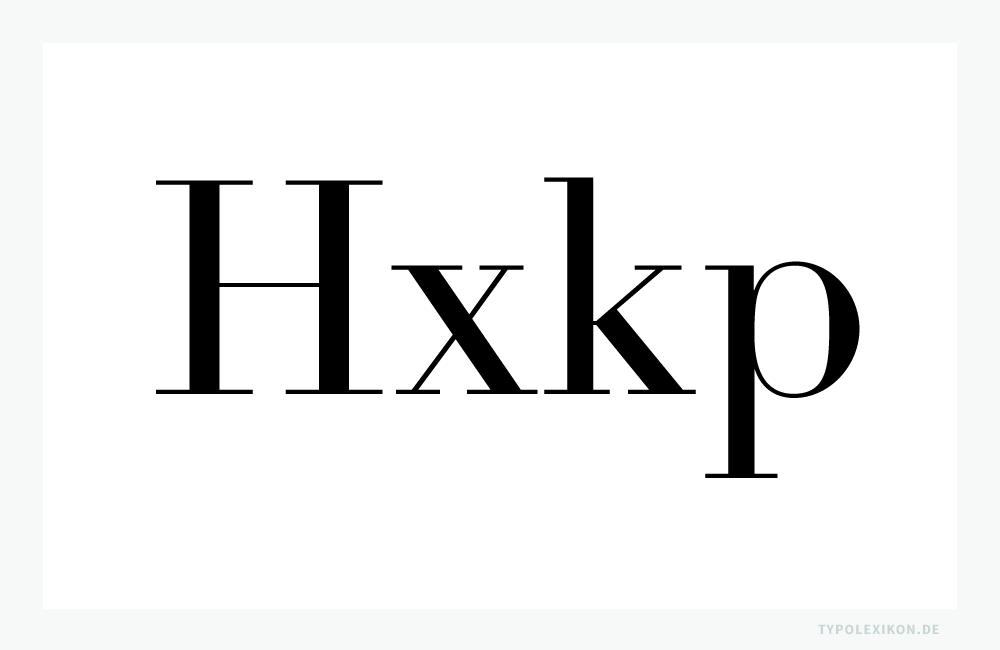
Klassizistische Antiqua
Schriftart; Schriftuntergruppe, die im Sinne der typografischen Schriftklassifikation zur Hauptschriftgruppe der Antiqua gehört; rundbogige Druckschrift römischen Ursprungs mit Serifen. Im englischsprachigen Raum als »Didone« bezeichnet.
Unter »Klassizistisch« bzw. »Klassizismus« wird ein westeuropäischer und nordamerikanischer Kunststil von 1750 bis ins frühe 19. Jahrhundert verstanden (Deutschland 1770–1830), der sich dadurch auszeichnet, die Formprinzipien der griechisch-römischen Antike in Kunst und Kultur nachzuahmen. In seiner typisch strengen Geradlinigkeit unterscheidet sich der Klassizismus wesentlich von der überbordenden Formenvielfalt des vorangegangenen Spätbarock bzw. Rokoko. Das Selbstverständnis dieses Stils: Logisch, klar, linear, streng und moralisierend. Politisch und gesellschaftlich symbolisierte der Klassizismus insbesondere die Demokratie des antiken Griechenlands und die römische Republik. So stellte er u.a. feudalistische Herrschaftsstrukturen und die »degenerierte Banausie« (Mirabeau) der Aristokratie in Frage und favorisierte das Ideal der liberalen Geisteshaltung eines humanistisch »aufgeklärten« Bildungsbürgertums (Gebrüder Humboldt). Der Klassizismus wurde deshalb zum führenden Kunststil junger Republiken wie Frankreich (Empire) und Nordamerika. Er galt ab den 1790er Jahren als »Stil der Revolution«. 1)
Etymologisch leitet sich der Begriff »Klassizismus« von »klassisch« ab, was aus dem mittellateinischen »classicus« für »mustergültig, vorbildlich, erstklassig « entlehnt ist, das wiederum auf das lateinische »classicus« (in normativer Hinsicht »die römische Bürgerklasse betreffend«) und »classis« zurückgeht, womit die »Klasse« als höchste, elitäre Gesellschaftsschicht der Antike gemeint war. Bereits im zweiten nachchristlichen Jahrhundert unterschied der römische Schriftsteller Aulus Gellius in seiner 20 Bände umfassenden griechisch-lateinischen Literaturgeschichte »Noctes Atticae « den »scriptor classicus«, also den erstklassigen Autor, Rhetor, Historiker oder Philosophen, schlicht: den Klassiker vom proletarischen Schreiberling. Im achtzehnten Jahrhundert wurde dieser Begriff dann auch auf nachantike Literaten und Künstler ausgedehnt, zuerst von Voltaire 1761, als er in einem seiner zahlreichen Artikel für Diderots »Encyclopédie« die bedeutendsten französischen Dichter des vorangegangenen Jahrhunderts – Corneille und Racine – als »Klassiker« bezeichnet.
Schriftprobe eines digitalen Remakes einer streng linear aufgebauten Klassizistischen Antiqua von Firmin Ambroise Didot (1764–1836) von Adrian Frutiger für Linotype aus dem Jahre 1991. Infografik: www.typolexikon.de
Schriftprobe eines digitalen Remakes einer streng linear aufgebauten Klassizistischen Antiqua von Firmin Ambroise Didot (1764–1836) von Adrian Frutiger (1928–2015) für Linotype aus dem Jahre 1991.
Die Bezeichnung »Antiqua« geht etymologisch auf die lateinische weibliche Form von »antiquus« zurück, für »vorig, alt«, eine Nebenform von »anticus« für »der vordere« vom lateinischen »ante« für »vor«. Mit »Antiqua« ist somit die »alte Schrift« gemeint. Die Antiqua ist heute die führende Verkehrsschrift der westlichen Welt.
Die Klassizistische Antiqua ist in ihrer Typometrie streng linearer aufgebaut. Sie verfügt über sehr starke Grundstriche, feine Haarlinien und feine, lange Serifen, welche waagrecht angesetzt sind und eckig abschließen. Die Schriftachse der runden Buchstabenformen steht präzise senkrecht.
Primäre Klassifikationsmerkmale
Dachansätze Majuskel: Gerade
Minuskeloberlängen: Enden bei der H-Linie, allerdings oft Dachansatz zur »Großen Überhangslinie«
Achse der Minuskel e: Waagrechter Innenbalken
Optische Achse der Rundformen: Senkrecht
Serifenübergänge: Eckig oder rund
Serifenseitenkante: Gerade
Serifenunterkante: Steht gerade auf der Grundlinie
Stichstärkenkontrast Balken/Querbalken: Sehr stark
Vertreter dieser Schriftart
SchriftSchriftgestalterFont FoundryJahr
Bauer BodoniJost, Heinrich
Höll, Lois
Bauer1926/1927
BodoniBodoni, GiambattistaStamperia realeum 1771
Bodoni Old FaceLange, Günter GerhardBerthold1983/2001
CaledoniaDwiggins, Wiliam A.Mergenthaler (Linotype)1939
CentennialFrutiger, AdrianLinotype1986
CenturyBenton, Linn BoydATF1894
DidotDidot, Firmin AmbroiseImprimerie Royaleum 1790
Didot LinotypeFrutiger, Adrian
Linotype Design Studio
Linotype1991
ElektraDwiggins, William A.Linotype1935
FeniceNovarese, AldoITC1977–1980
FilosofiaLicko, ZuzanaEmigre1996
Monotype ModernMonotype1860/1896
Prillwitz, Johann Carl LudwigGöschen/Bertuch1790
PrillwitzPreuss, IngopreussTYPE2006
Romain de L’Empereur
(Kaiser-Antiqua)
Didot, Firmin AmbroiseImprimerie Royale1804
WalbaumWalbaum, Justus ErichKircher/Walbaum/Bertuchum 1800
WalbaumLange, Günter GerhardBerthold1976
Ab cirka 1770 entwickelte der italienische »Principe dei tipografi« (»der Fürst unter den Typografen«) Giambattista Bodoni (1740–1813) aus der französischen Réales Pierre Simon Fourniers erstmals eine Klassizistische Antiqua mit einem streng symmetrischen, fast monumental anmutenden Aufbau, welche die westeuropäische Schriftkultur des gesamten 19. Jahrhunderts maßgeblich prägen sollte. Erstmalig wurde diese Schriftart von Bodoni in seinen »Epithalamia exoticis linguis reddita, Parmae, Regio typografeo MDCCLXXV« 2)  veröffentlicht, und in den darauf folgenden Jahren verfeinert.
Schriftprobe eines digitalen Remakes der Bodoni (Giambattista Bodoni, 1740–1813). In der Schriftklassifikation zählen Bodonis zu den Klassizistischen Antiquas. Infografik: www.typolexikon.de
Schriftprobe eines digitalen Remakes der Bodoni (Giambattista Bodoni, 1740–1813). In der Schriftklassifikation zählen Bodonis zu den reinen Klassizistischen Antiquas.
Schrift ist nicht gleich Schrift, auch wenn Schriften auf den ersten Blick ähnlich aussehen können oder vordergründig sogar den gleichen Namen tragen. Hier ein Rohsatzvergleich von vier Bodoni Antiquas im normalen Schriftschnitt. Die Typometrie unterscheidet sich signifikant voneinander. Infografik: www.typolexikon.de
Schrift ist nicht gleich Schrift, auch wenn Schriften auf den ersten Blick ähnlich aussehen können oder vordergründig sogar den gleichen Namen tragen. Hier ein Rohsatzvergleich von vier klassizistischen Bodoni Antiquas im normalen Schriftschnitt. Die Typometrie unterscheidet sich signifikant voneinander.
In Deutschland (damals Heiliges Römisches Reich Deutscher Nation 962–1806) war es vornehmlich der Leipziger (damals Kurfürstentum Sachsen) Typopgraph und Verleger Georg Joachim Göschen (1752–1828), der in den Jahren 1794 bis 1802 die Gesamtausgabe der Werke von Christoph Martin Wieland in der 1790 von Johann Carl Ludwig Prillwitz (1758–1810) geschnittenen ersten deutschen Klassizistischen Antiqua verlegte und in exemplarischer Weise die Eleganz der französischen Lettern von Firmin Didot (1764–1836) mit den buchtypografischen Stilvorgaben und Satzregeln, die Bodoni in seinem »Manuale tipografico« kanonisiert hatte, umsetzte. Zur Realisierung seiner makro- und mikrotypografischen höchst anspruchsvollen Formvorstellungen von einer ebenmäßigen, sogenannten »splendiden Satzweise« führte Göschen auch die dazugehörige Drucktechnologie ein: der Einsatz von Stegen und Pressen aus Metall anstelle von Holz gewährleistete das konsequente Halten der Schriftlinie, den exakten Axialsatz des Titelblatts und den gleichmäßigen Farbabdruck; ein optimiertes Schriftgußverfahren ermöglichte die präzisen und langgezogenen Haarstriche der neuen Antiqua-Schnitte; sorgfältigst ausgeschlossene Buchstaben- (Laufweite) und Wortzwischenräume, ein großer Zeilendurchschuß und die breiten Ränder des Satzspiegels sorgten für die regelmäßige Grauwirkung eines lichten, harmonischen Satzbildes, das insgesamt dem ästhetischen Ideal des klassizistischen Stils entsprach. Voll begeisterter Emphase schrieb Wieland 1793 in einem Brief an Göschen über den Probedruck der Prillwitz-Antiqua für die Ausgabe seiner Werke: »Ich kann mich nicht genug an der Schönheit dieser Lettern ergötzen! Eine jede ist in ihrer Art eine Mediceische Venus. Lachen Sie nicht über die anscheinende Hyperbole! Es ist etwas Wahres an dieser seltsam tönenden Behauptung; ich wenigstens kann mir keine schöneren Schriftzeichen denken als diese, und ich habe doch auch eine Imaginazion …«
1804 schuf Firmin Didot in Paris für die offiziellen Dokumente zur Kaiser-Krönung von Napoleon Bonaparte den nur dieses eine Mal verwendeten Schriftschnitt »Romain de L’Empereur« ( »Kaiser-Antiqua« ). Diese exklusive Klassizistische Antiqua präsentierte als typografisches und kulturpolitisch gleichermaßen brisantes Kuriosum die englischen, üblicherweise hochgestellten Anführungszeichen in der niedrigeren Position der traditionellen französischen Guillemets, also »99/66« in Minuskelhöhe: wohl als »diakritisch« subtile Anspielung darauf, dass Napoleon den permanent feindseligen Engländern eben erst den Friedensvertrag von Amiens abgetrotzt hatte, eine von Britannien aus gegen ihn angezettelte Verschwörung vereitelt hatte und siegesgewohnt damit rechnete, binnen kurzem ganz England unter seine Herrschaft zu bringen. Didots Kaiser-Antiqua ist eines von vielen Beispielen dafür, dass »Schriftzeichen« stets auch »Zeitzeichen« sind.
Parallel zur Typografie verwendeten insbesondere Kupferstecher (Tiefdrucker) diese Schriftart gerne, weil die Klassizistische Antiqua aufgrund ihrer Typometrie leichter mit dem Grabstichel auf die Kupferplatte zu »stechen« bzw. zu gravieren (Gravure) war, als eine Renaissance- oder Vorklassizistische Antiqua. Inwieweit die Technik des Kupferstichs die Entwicklung der typografischen Klassizistischen Antiqua beeinflusst hat, ist wissenschaftlich nicht dokumentiert. 3)
Auf Dauer konnte sich die deutsche Klassizistische Antiqua (außer für bibliophile Luxusausgaben der Hochliteratur) gegen die Dominanz der Fraktur allerdings nicht behaupten, war doch das breite Lesepublikum jahrhundertelang fast ausschließlich auf das gebrochene Schriftbild fixiert gewesen. Absatzschwierigkeiten und hohe verlegerische Verluste waren die unausbleibliche Folge. Dazu kamen die Napoleonischen Kriege, in deren Verlauf der deutsche Nationalismus mehr und mehr erstarkte, wodurch die als französische und damit feindliche Schrift konnotierte Antiqua bis spätestens 1812 jegliche Akzeptanz verlor.
In England entstand um 1817 aus der von Firmin Didot perfektionierten Klassizistischen Antiqua die »Egyptienne« und fast zeitgleich die »Grotesk«.
© Wolfgang Beinert, www.typolexikon.de
↑1 Anmerkung: Bedeutende Vertreter der klassizistischen Stilepoche waren u.a. Piranesi, Karl Friedrich Schinkel und Leo von Klenze (Architektur), Jacques-Louis David (Malerei), Antonio Canova (Bildhauerei), Johann Wolfgang von Goethe und Friedrich Schiller (Literatur), Wolfgang Amadeus Mozart und Ludwig van Beethoven (Musik), Wilhelm von Humboldt (Wissenschaft) sowie Firmin Didot und Giambattista Bodoni (Typografie).
↑2 Anmerkung: Facsimile des Bodoni-Drucks mit einer Klassizistischen Antiqua, Parma 1775, aus der Cary Collection, New York unter . Melbert B. Cary war in den 1920er Jahren Direktor der Continental Type Founders Association; seine Sammlung umfaßt rund 2.300 bedeutende Werke zur Geschichte des Buchdrucks und gehört zum Rochester Institute of Technology.
↑3 Anmerkung: Die in der »Schriftsetzerliteratur« immer wieder reproduzierte Binsenweisheit, dass sich die Klassizistische Antiqua um 1800 aufgrund des Gebrauchs der »Spitzfeder« entwickelt hat, ist – philologisch betrachtet – absoluter Nonsens.